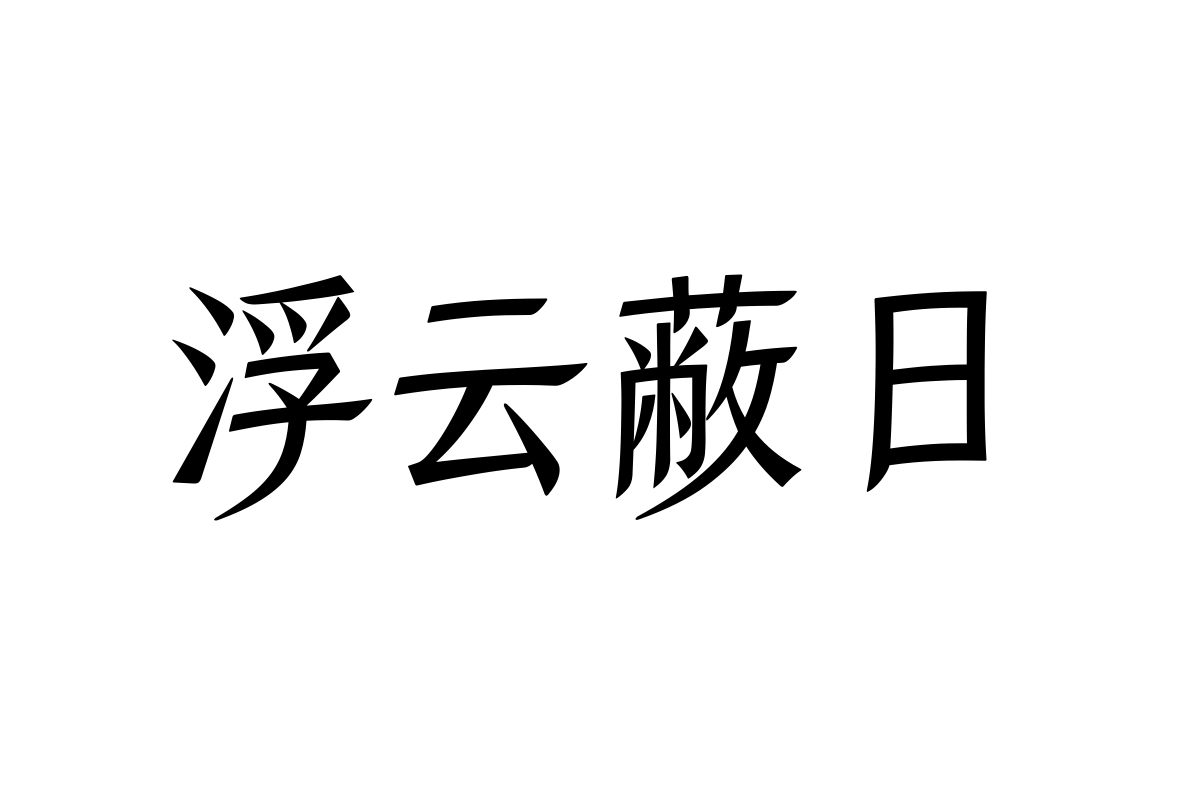
汉仪风竹体是一款由汉仪公司设计开发的中文字体,具有独特的风格和特点。这款字体采用了传统的书法风格,笔画流畅自然,字形结构紧凑而富有变化。它的线条粗细不一,既有粗犷的笔触,也有细腻的过渡,给人一种古朴典雅的感觉。
汉仪风竹体的字体特点主要体现在以下几个方面:
1. 笔画流畅:汉仪风竹体的笔画线条流畅自然,没有生硬的折线,给人一种轻松愉悦的阅读体验。
2. 字形结构紧凑:这款字体的字形结构紧凑,每个字的笔画都紧密相连,形成了一种独特的视觉效果。
3. 风格独特:汉仪风竹体采用了传统的书法风格,笔画粗细不一,既有粗犷的笔触,也有细腻的过渡,给人一种古朴典雅的感觉。
4. 适用范围广泛:这款字体适用于各种印刷品和电子屏幕显示,如报纸、杂志、书籍、广告、网页等。
总之,汉仪风竹体是一款具有独特风格的中文字体,适合用于需要展现传统文化特色的场合。